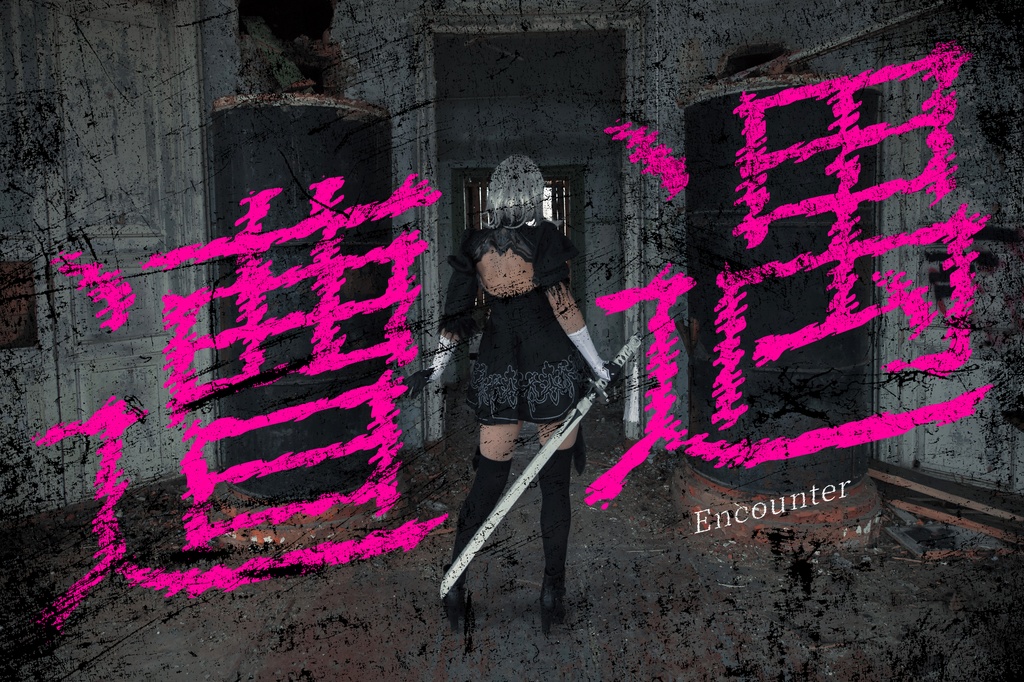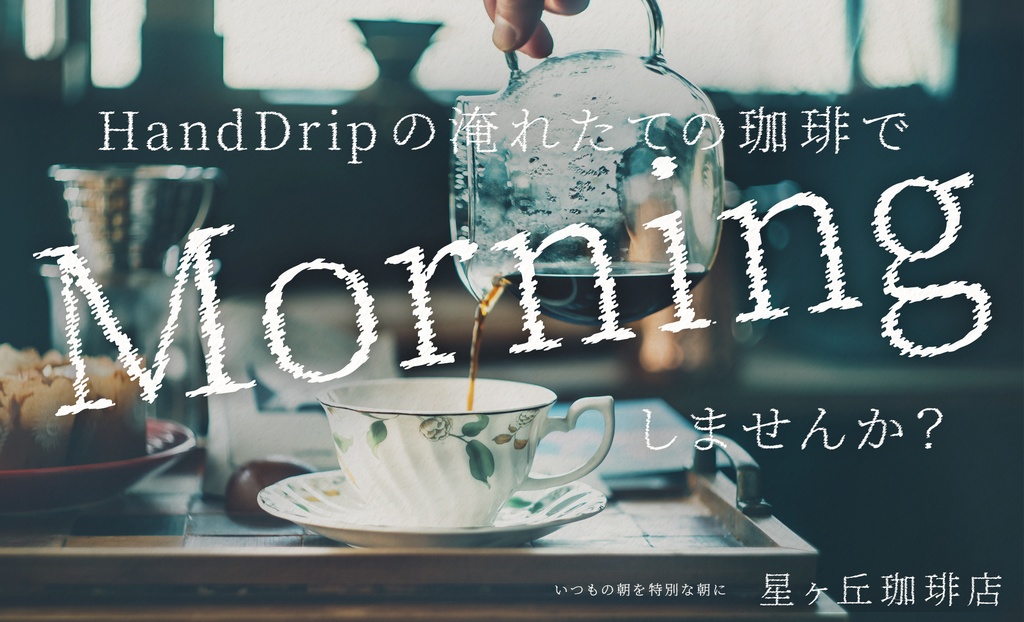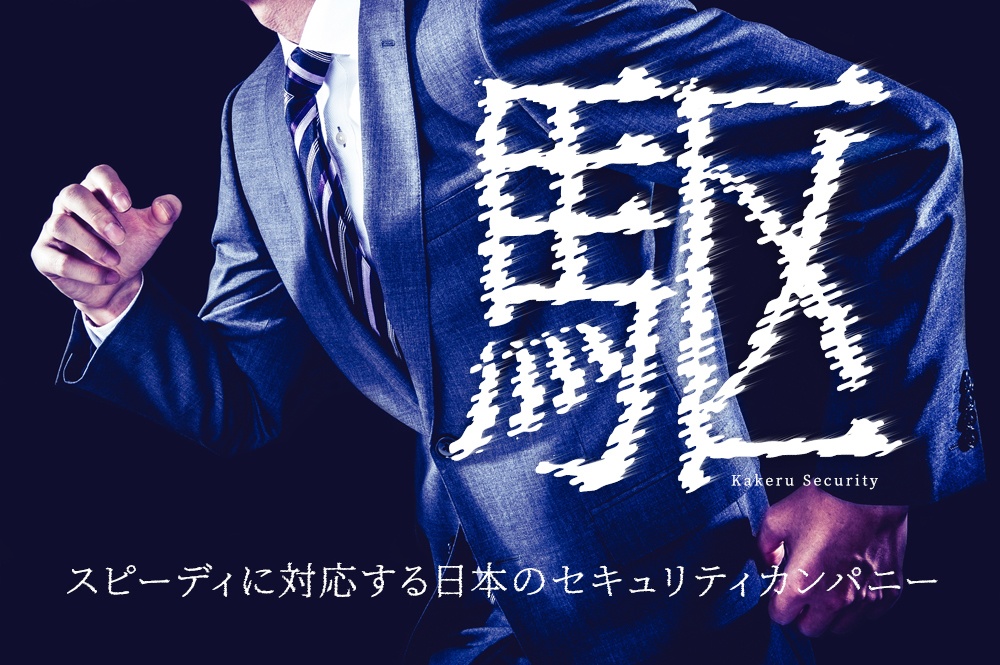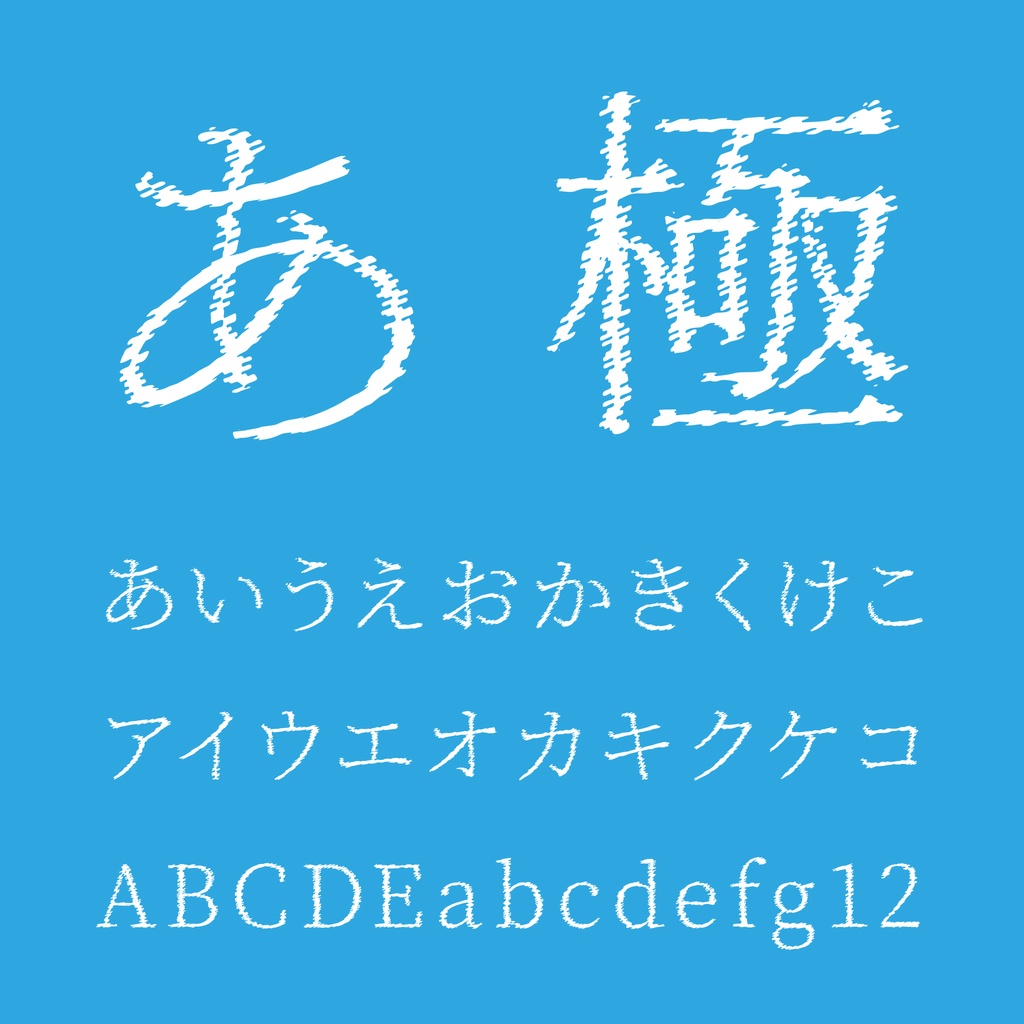
瞬きノ明朝(フリーフォント)
瞬きノ明朝(またたきのみんちょう)は、文字がギザギザに揺れているインパクトのあるフォントです。見出し・ロゴにピッタリのデザイン。 文字数は8000字以上揃っていますので、安心してお使い頂けます。 ■フリーフォント使用に当たって フォントをインストールして頂くとパソコンのワープロ、グラフィックソフトなどのアプリケーションを使って自由にデザイン、印刷することができます。個人利用・商用利用にかかわらず、無償で使用することができます。当フォントはSIL Open Font License 1.1のオープンソースライセンスに準じます。 ■瞬きノ明朝の概要 瞬きノ明朝は「源ノ明朝」のフォントを改変して制作した派生フォントです。 制作に関わる全ての方に深くお礼申し上げます。 当フォントはFontlabStudio、武蔵システム(http://opentype.jp/)OTEditで作成しました※フリーフォントのインストール・ソフトでの使用についてのサポート・お問い合せは受け付けません。 ⚠️このフォントは自由に動画に使えるフォントです。ご利用の際は次のクレジットを入れていただけると、ものすご〜く喜びます! –––––––––––––––––––––––––––––– フォント:瞬きノ明朝 フリーダウンロード:https://flopdesign.booth.pm/items/3793828 –––––––––––––––––––––––––––––– フォローしてください。 Instagram ▶ https://www.instagram.com/flopdesign.font/ X ▶ https://twitter.com/flopdesign